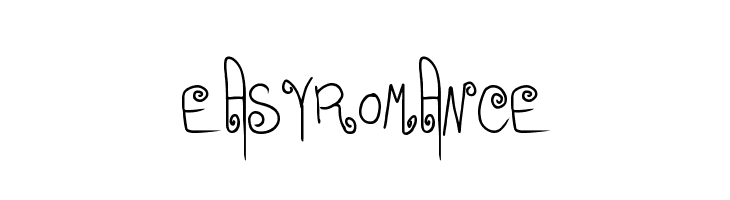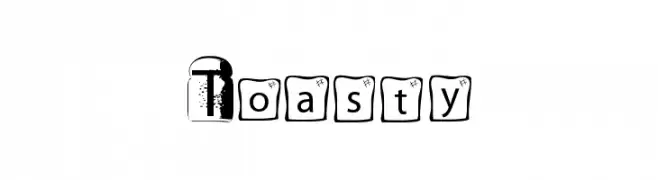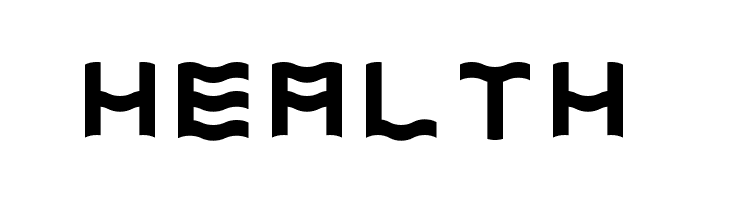
每款 新字体 都有独特个性:从干净现代的无衬线到富有表现力的手写体、醒目的展示体。 我们频繁更新列表,你可以先在线预览再免费下载使用。
A playful, graffiti-inspired outline font with a bold and artistic style.
A clean, rounded font with even spacing and subtle stroke variations.
A playful, hand-drawn font with a whimsical and casual style.
A playful, hand-drawn font with bold, rounded edges and a cartoonish style.
现在大家都在用哪些新字体?
流行变化很快,但极简无衬线与个性鲜明的展示体当前更受欢迎, 特别适合移动端内容与现代品牌风格。
有哪些值得尝试的 5 款新字体?
近期热门包括 Toasty, Party Time, Graff, Magic Christmas and HelvetiHand 它们在清晰度与个性之间取得平衡,适用于科技品牌、编辑排版与社媒视觉。